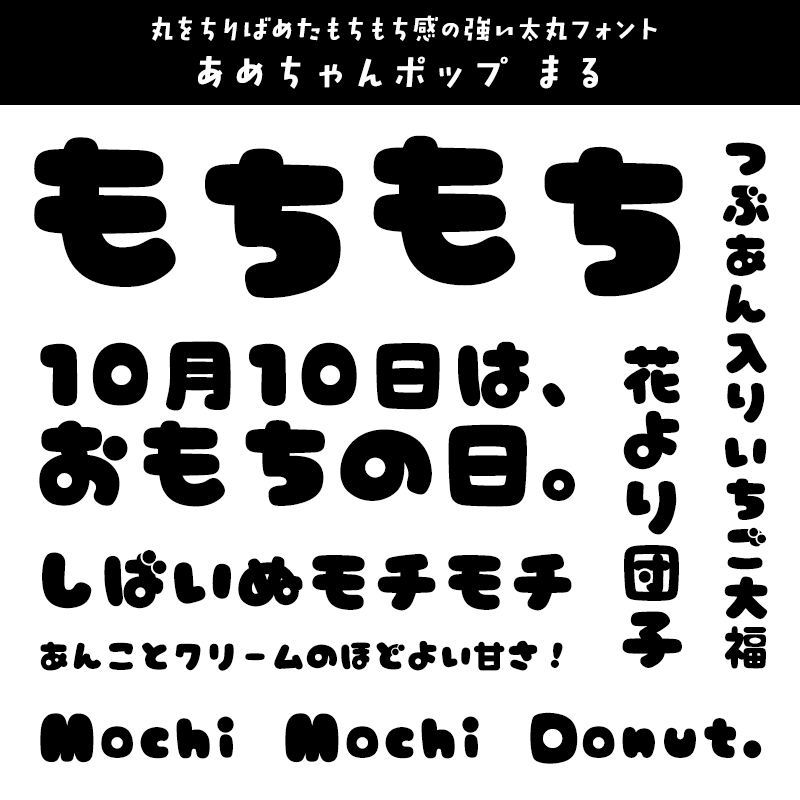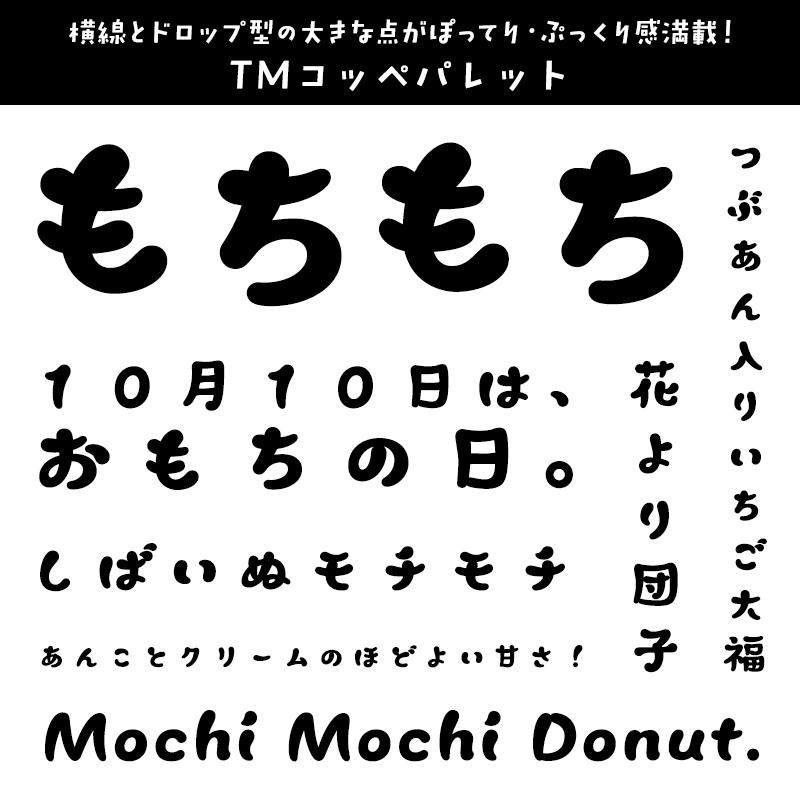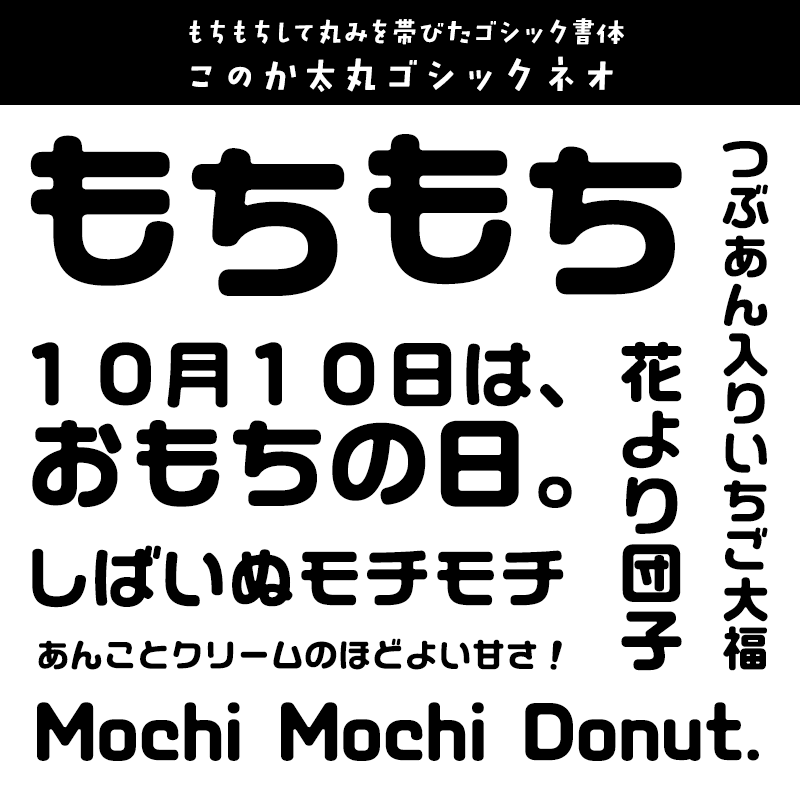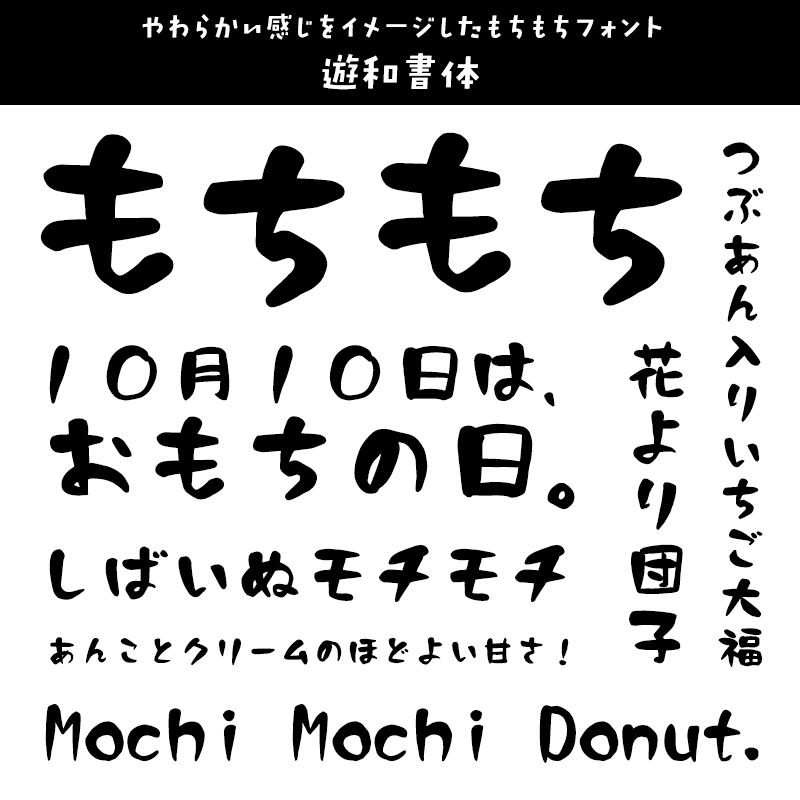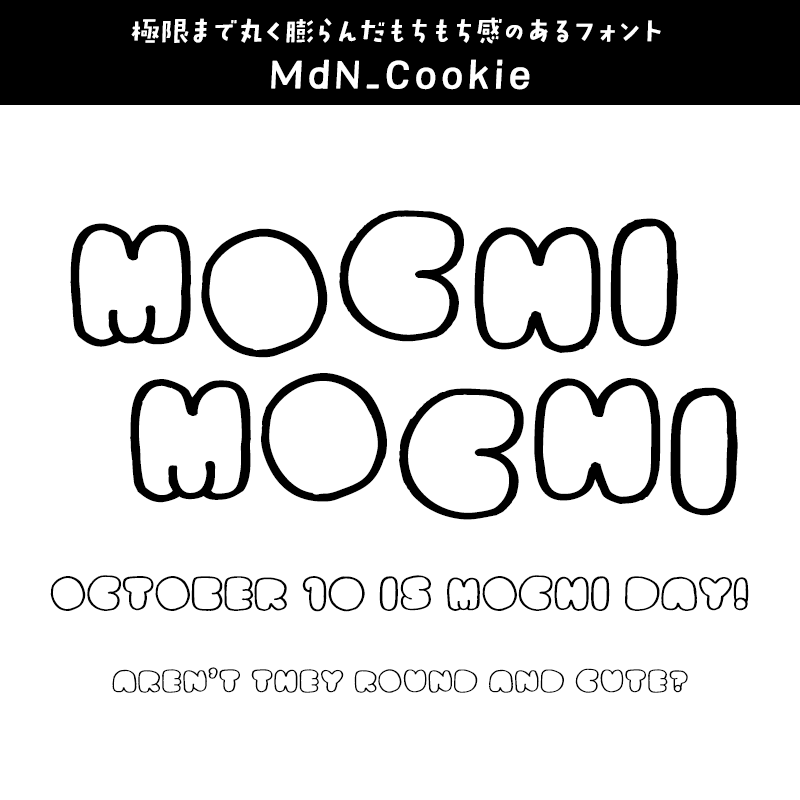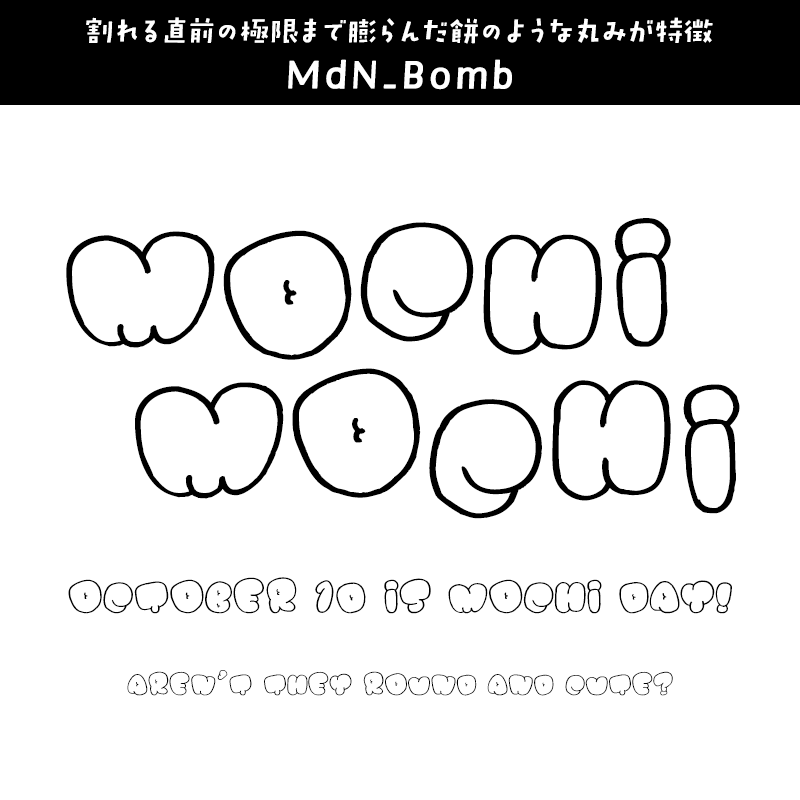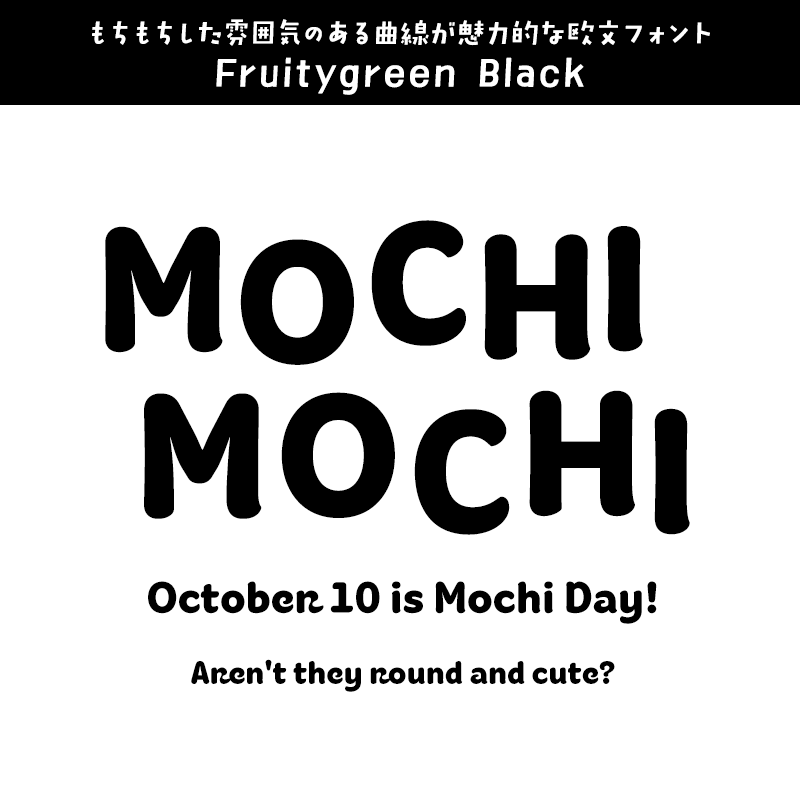
もちもちに合うフォント:特化型 目的別フォントガイド #067
今回はもちもちに合うフォント。日々フォントのことばかり考えている当店スタッフが直感的に選んだフォントをご紹介します。
もちもちに合うフォントをスタッフが選びました
もちもちに合うフォント イワタ福まるご E
低めの重心、ユニークな丸みが特徴的なもちもちフォント
イワタ福まるご E【イワタ書体ライブラリー】
もちもちに合うフォント イワタ福まるご E
有機的な曲線で構成された、これまでにないシルエットの丸ゴシック体。「もっちりぽってり」見出しから、しっかり文字組までこなせます。
もちもちに合うフォント DSくるみるく
ふっくらして可愛い!もちもち感のあるフォント
DSくるみるく【七種泰史/デザインシグナル】
もちもちに合うフォント DSくるみるく
ゴロゴロ、ホロホロ。ふっくら、ほっこり。手づくりクッキーやパンのようなイメージで。不揃いの中にも味のある書体です。
もちもちに合うフォント DSマンボ
雲の様にふんわり・もちもちっとしたデザイン書体
DSマンボ【七種泰史/デザインシグナル】
もちもちに合うフォント DSマンボ
やさしさと楽しさをもった、動きのある書体です。おトクな マンボ・ルンバ 2書体セット もあります。
もちもちに合うフォント あめちゃんポップ まる
丸をちりばめたもちもち感の強い太丸フォント
あめちゃんポップ まる【かに沢のりお】
もちもちに合うフォント あめちゃんポップ まる
まるをあちこちに散りばめた、ぽってりかわいいポップな太めのフォントです。
もちもちに合うフォント TMコッペパレット
横線とドロップ型の大きな点がぽってり・ぷっくり感満載!
TMコッペパレット【タンデムフォント】
もちもちに合うフォント TMコッペパレット
画数によって大きさが異なる、ふんわりぽってりしたデザイン書体です。特典として、Adobe Illustratorに対応したカラーフォントを同梱。
もちもちに合うフォント このか太丸ゴシックネオ
もちもちして丸みを帯びたゴシック書体
このか太丸ゴシックネオ【CFONT】
もちもちに合うフォント このか太丸ゴシックネオ
ファンシーな優しい書体をイメージしてデザインされたフォント。キャッチコピーやコメントをやわらかい印象にしたいときにおすすめです。
もちもちに合うフォント DF唐風隷書体 W9
落ち着きを感じさせるもちもち隷書体フォント
DF唐風隷書体 W9【ダイナフォント】
もちもちに合うフォント DF唐風隷書体 W9
横長で太く扁平な字形がどっしりと落ち着きを感じさせる「隷書体」です。中華風を表現したい場面や古典的なテイストの表現したい場面などに適しています。
もちもちに合うフォント ヒラギノ丸ゴオールド W8
親しみやすくどこか懐かしい、もちもちフォント
ヒラギノ丸ゴオールド W8【ヒラギノフォント】
もちもちに合うフォント ヒラギノ丸ゴオールド W8
これまでにないユニークで個性的な丸ゴシック体です。一本の線の中に細太の抑揚がしっかりとついており、線端がぷっくりと太くなる独特のデザインが、単純に見えがちなカタカナなどの表情を豊かにしています。ひと目で惹きつける特徴を持ちながらも、親しみやすくどこか懐かしい独特のたたずまいがあり、タイトルや見出し、短い文章に使ってじっくり味わいたいフォントです。
もちもちに合うフォント DF円楷書 W10
太く丸みがあり穏やかさを感じるもちもち筆文字
DF円楷書 W10【ダイナフォント】
もちもちに合うフォント DF円楷書 W10
太く丸みのある筆勢により穏やかな一面と力強さを兼ね備えた楷書体です。
もちもちに合うフォント 横丁&鍛所 あまからフォント
親しみやすいもちもち感、丸みを帯びた筆文字書体
横丁&鍛所 あまからフォント【六葉情報】
もちもちに合うフォント 横丁&鍛所 あまからフォント
あまからフォントは、丸みを帯びた極太の毛筆書体で、暖かくて優しい親しみやすい印象を持っています。タイトルや見出し、ロゴなどにおすすめです。
もちもちに合うフォント 遊和書体
やわらかい感じをイメージしたもちもちフォント
遊和書体【昭和書体/コーエーサインワークス】
もちもちに合うフォント 遊和書体
ほのぼの、ふわふわ、もちもちとしたやわらかい感じをイメージしたフォント。従来の綱紀栄泉氏が揮毫する本格的な毛筆書体(昭和書体シリーズ、高解像度書体)とは違い、デザイナーが自由な発想でデザインした少し遊び心の入った書体です。
もちもちに合うフォント DSゆたんぽ
独特のハネがもちもち感あふれるフォント
DSゆたんぽ【七種泰史/デザインシグナル】
もちもちに合うフォント DSゆたんぽ
ぬくぬく、ポカポカ。こころの奥まであたたかさを感じるような書体を目指して作られたデザインフォント。
もちもちに合うフォント mini-コンビニ
楽しくかわいい、もちもち丸い仮名フォント
mini-コンビニ【miniyama】
もちもちに合うフォント mini-コンビニ
もちもちに合うフォント MdN_Cookie
極限まで丸く膨らんだもちもち感のあるフォント
MdN_Cookie【MdN DESIGN】
もちもちに合うフォント MdN_Cookie
焼き上がったクッキーのように大きく丸く膨らんだ欧文書体。〝女子的〟手書き文字を素材集にした2013年発行の書籍「流行型女子文字素材集 女子タイポ。」の付属CD-ROMに収録されているデータの個別販売です。
もちもちに合うフォント MdN_Bomb
割れる直前の極限まで膨らんだ餅のような丸みが特徴
MdN_Bomb【MdN DESIGN】
もちもちに合うフォント MdN_Bomb
その名の通り爆発する直前の爆弾のような膨れ上がった欧文書体。〝女子的〟手書き文字を素材集にした2013年発行の書籍「流行型女子文字素材集 女子タイポ。」の付属CD-ROMに収録されているデータの個別販売です。
もちもちに合うフォント VAG Rounded™ Next ExtraBlack
丸みのあるストロークの終端が特徴的なもちもちサンセリフ
VAG Rounded™ Next ExtraBlack【Monotype】
もちもちに合うフォント VAG Rounded™ Next ExtraBlack
VolkswagenのCI用フォントとして設計されたサンセリフ。丸みのあるストロークの終端が特徴です。
もちもちに合うフォント Fruitygreen™ Black
もちもちした雰囲気のある曲線が魅力的な欧文フォント
Fruitygreen™ Black【Linotype】
もちもちに合うフォント Fruitygreen™ Black
Fruitygreenは、果物が持つユニークで魅力的な曲線などの部分的な特徴をもとにデザインされたフォント。丸みを帯びた文字が一見筆で書かれたカリグラフィー書体のように感じさせる個性的なデザインフォントです。